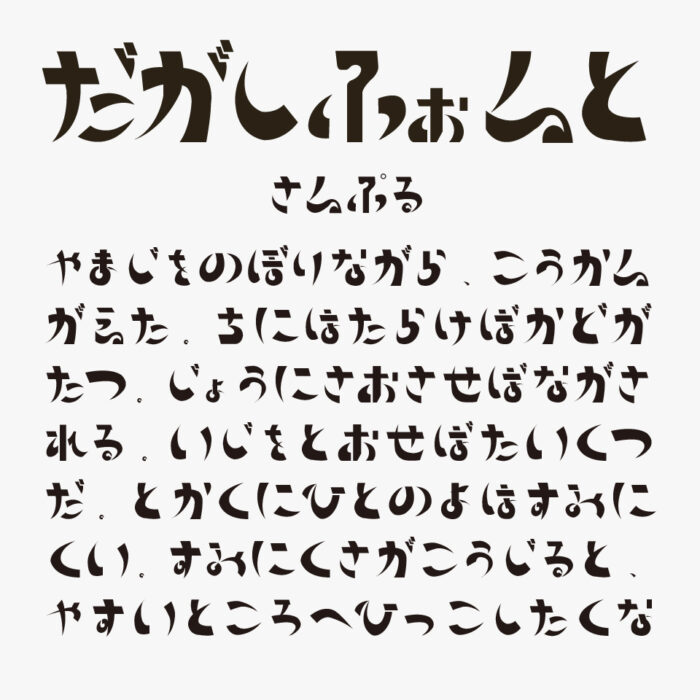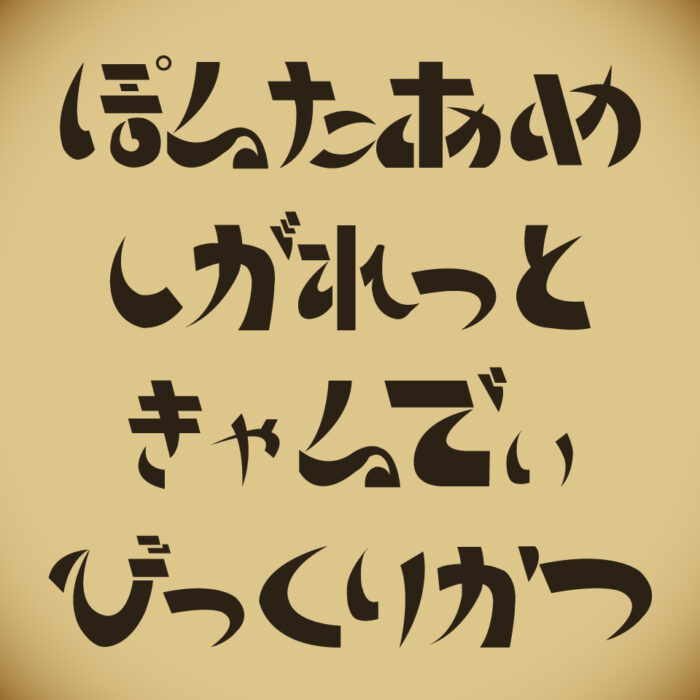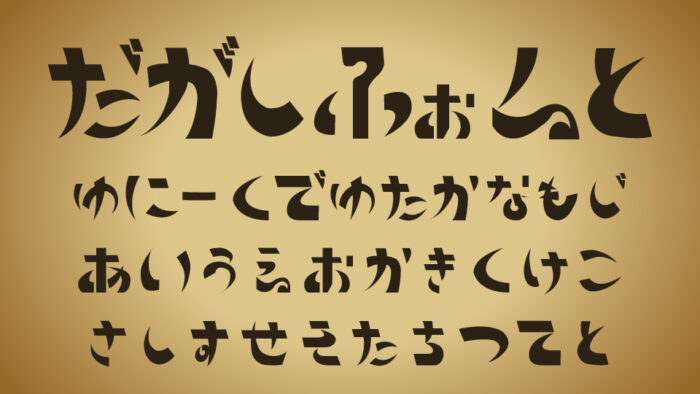
だがしふぉんとは、勢いのある筆づかいと一文字ごとにユニーク形状が絶妙に混ざり合った、レトロで遊び心たっぷりなひらがなフォントです。
駄菓子屋や縁日など、昭和のレトロ感や懐かしさを感じられる遊びココロのあるデザインがとてもステキです。
文字ごとにリズム感のあり、にょきっと伸びた「し」や、跳ねるような「と」など、見ていて楽しい表情が魅力的なフォントです。
駄菓子や縁日な雰囲気が、なんだか懐かしい気持ちになるレトロなフォントです。
収録文字は、ひらがなのみ収録されています。